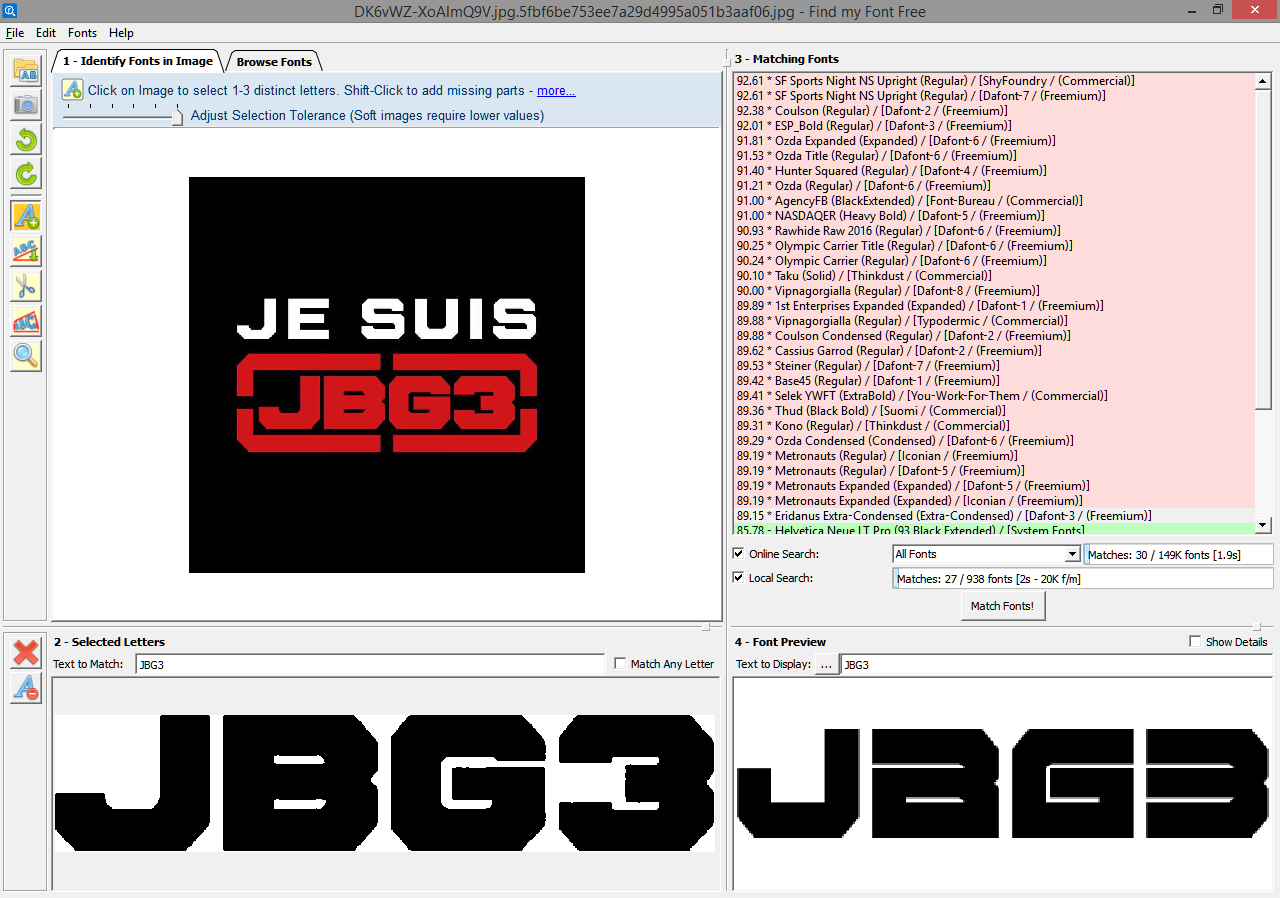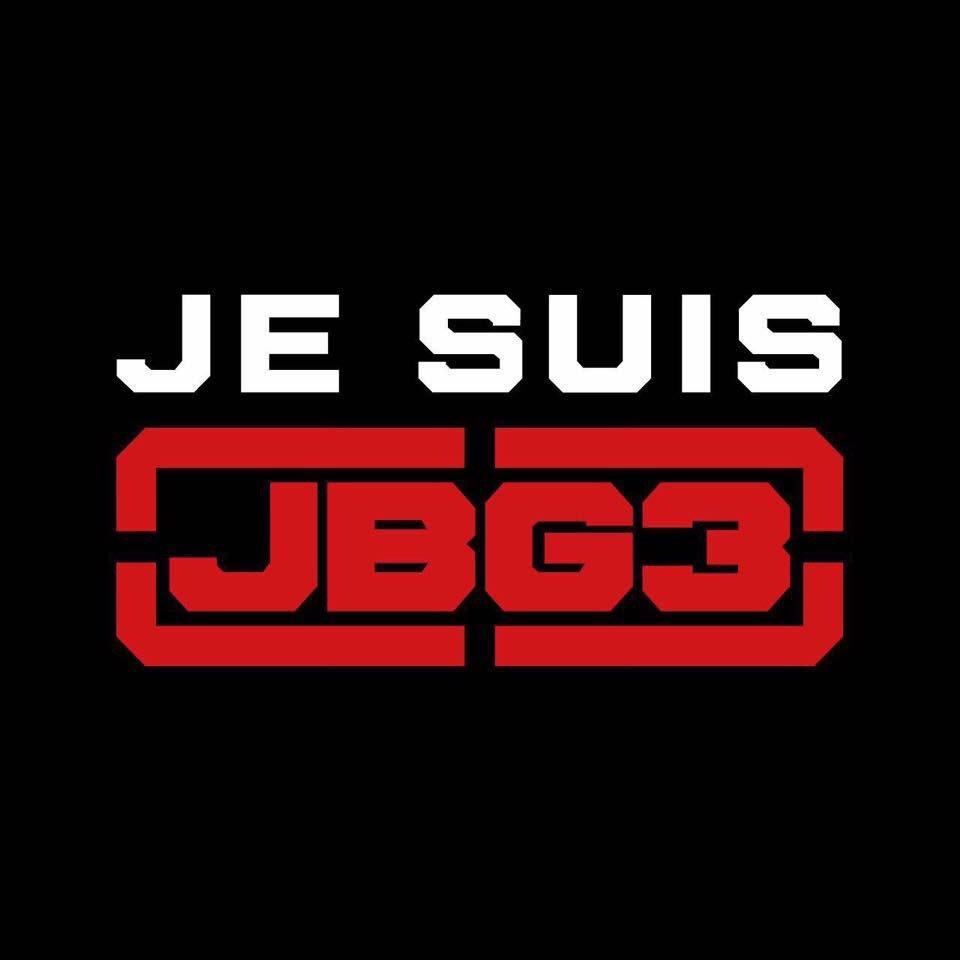
Ich suche die Schriftart von JBG 3?
wie schon im Betreff erwähnt suche ich die Schriftart von JBG 3 (siehe Bilder). Natürlich kann es auch eine sehr ähnliche Schriftart sein. Könnt Ihr mir da vielleicht weiter helfen?
Ich vermute mal das es sich hierbei um eine selbstgemachte Schriftart handelt. Also falls das so ist, kann man es ja vergessen die genaue Schriftart zu bekommen.
Aber falls es ähnliche Schriftarten gibt (zum Kauf oder sogar kostenlos! Natürlich legal!) würde ich das auch gerne wissen wie die Schriftart heißt.
PS: Auf Seiten wie WhatTheFont (auf myfonts) habe ich auch schon geschaut. Die spucken mir leider die Schriftart nicht raus. Die angeblichen Schriftarten die zu diesem Bild gefunden werden ähneln kein bisschen.
Schau mal hier:
https://www.dafont.com/de/theme.php?cat=104
da und auf den Folgeseiten ist einiges entfernt ähnliches. Ich hab das nicht alles durch gesehen, gut möglich das da auch genau die steckt.